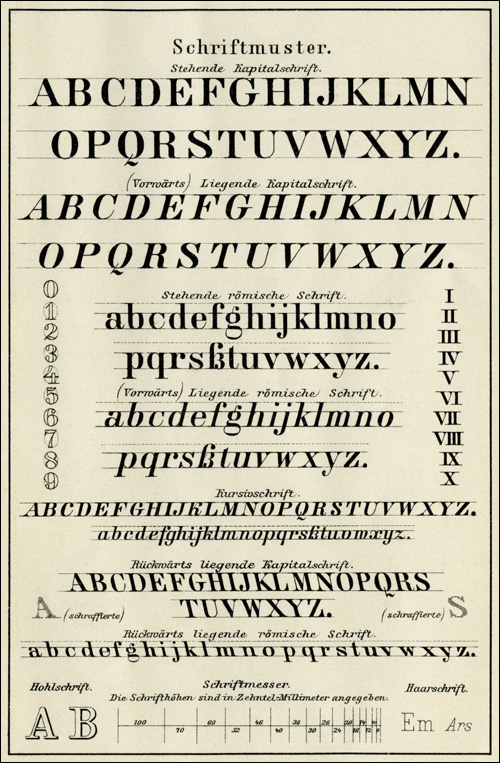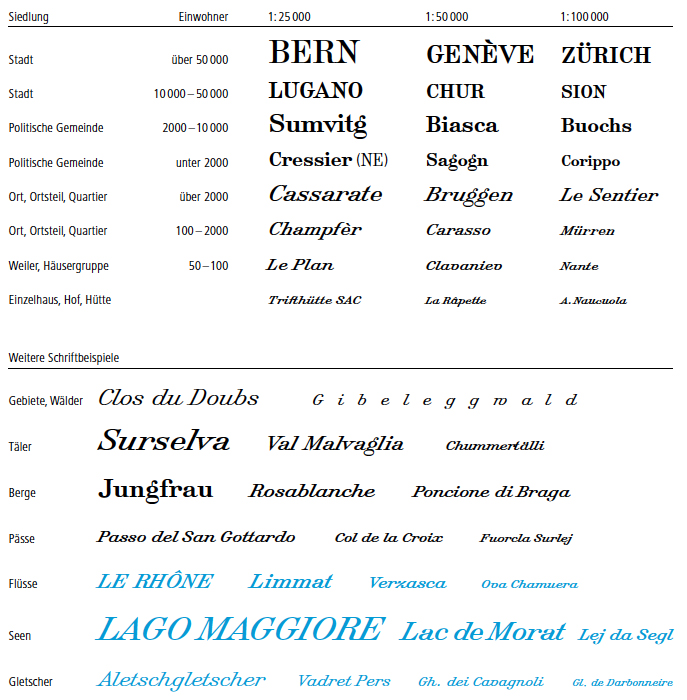
Schriften Schweizer Landeskarten vor Redesign 2014
Weiss jemand welche Schriften in den Schweizer Landeskarten (vor dem Redesign 2014) verwendet wurden?
Spezielle Merkmale sind das kleine "z" welches wie ein "x" aussieht und das offene "g" in der kursiven Version. Siehe Schrift in blau. Allerdings gibts auch das geschlossene "g"...
Auf welcher Basis diese Schriften erstellt wurden, weiß ich nicht.
Seit 2014 wird die "Frutiger Neue LT Pro" verwendet.
Die Basis dieser S chriften sind alte, noch als Kupferstich erstellte Landkarten, der besondere Duktus dieser Kupferstich-Römisch wurde dann auch für neuere Landkarten ünernommen, und auch als Bleisatzschriften verfügbar gemacht, und sind heute u.A-. bei Linotype (jetzt ja Monotype) zu haben, auch linksgeneigt, die auf Landkarten oft zur Kennzeichnung von gewässern verwendet werden, wenn nicht, wie in deinem Beispiel dann hierzu die Schriftfarbe genutzt wird.
Die Basis dieser Schriften sind alte, noch als Kupferstich erstellte Landkarten, …
Das war schon klar :-) Ich meinte, ob es eine bestehende Schrift als Basis dafür gibt.
Was spricht gegen die von catfonts gepostete "Römisch"?
Zur Landkartenschrift Römisch gibt es aber auch einen echten Kursiv-Font zu diesem Landkarten-Schriftenpaket, um möglichjst viwele landkaretentypische Auszeichnungen für Ortsnamen, Flurnamen, Gewässern, Landmarken usw zu haben neben der unterschiedlich fetten aufrechten Schrift mit dem dreistöckigen g sowohl rechts- und linksgeneigte, wie auch echte, teilverbundene Kzursivschnitte auch in Linksneigung: